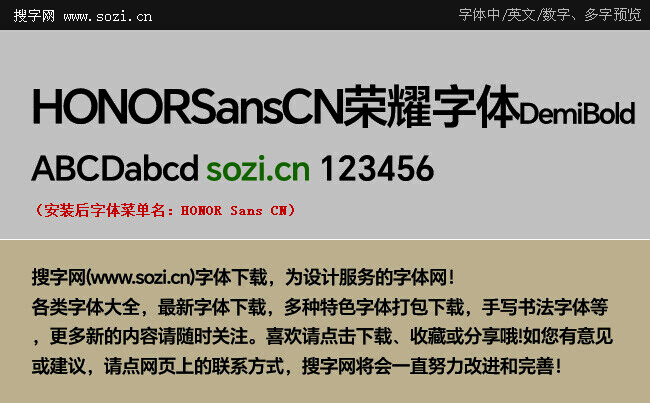
HONORSansCN榮耀字體DemiBold
搜字網(wǎng)給大家提供一款HONORSansCN榮耀字體DemiBold中文字體下載,榮耀字體HONOR Sans是由榮耀MagicOS聯(lián)手方正帶來的一套全新的免費可商用中文字體,包含了 9 種字重,HONOR Sans擁有簡潔生動的筆劃以及平滑優(yōu)美的曲線,相比標準的黑體則在筆畫的曲率、結構布局上進行了優(yōu)化,很好地提升了可讀性以及文字辨識度,讓排版更加舒服,看起來也更加優(yōu)雅,能有效降低長時間閱讀時對視覺造成的疲勞。 適用于標題設計、海報設計、書籍排版以及網(wǎng)頁設計等應用。